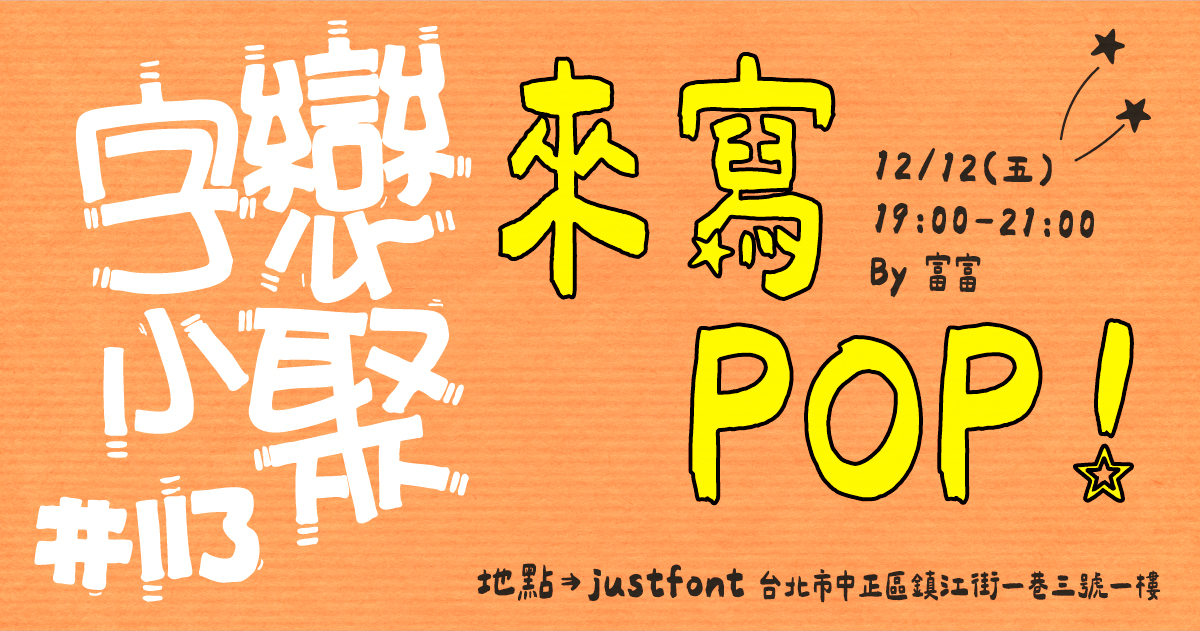
字戀小聚 #113|來寫 POP!
超可愛又有點 Y2K 的 POP 風格起源於店面手繪版
在數位印刷超便利的現在變得稀有又吸睛
本次字戀小聚要來一起寫 POP
從基本筆法開始練習
最後可以完成自己的小小作品💖
活動內容
🖌️ POP 的書寫工具
🖌️ 常見字體介紹
🖌️ 常見描邊方式
🖌️ 實際寫寫看